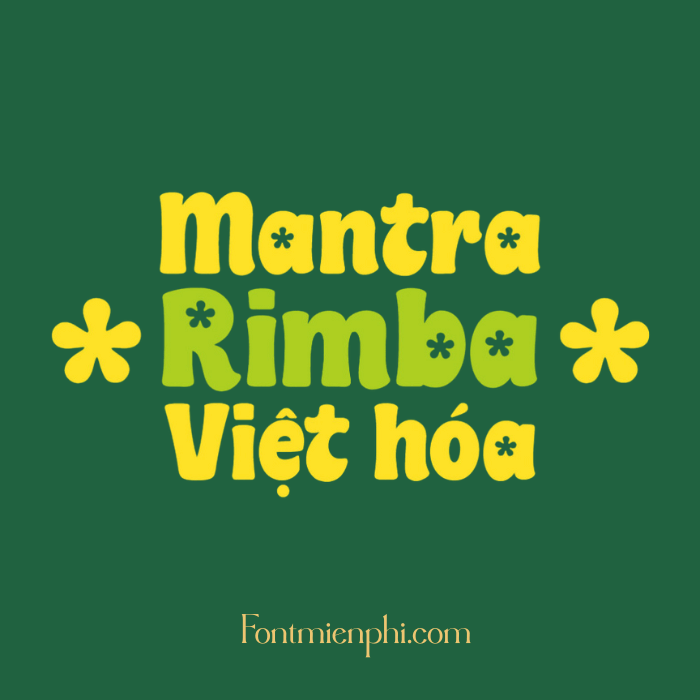
Font Việt hóa 1FTV VIP Mantra Rimba – Phong Cách Độc Đáo Cho Thiết Kế
Font Việt hóa 1FTV VIP Mantra Rimba là bộ font chữ nghệ thuật độc đáo, được thiết kế với phong cách hoang dã, phóng khoáng, phù hợp cho các dự án sáng tạo như poster, logo, bìa sách, và hình ảnh quảng cáo. Với nét chữ uốn lượn tự nhiên, Mantra Rimba mang đến cảm giác mạnh mẽ, cá tính, giúp sản phẩm thiết kế của bạn nổi bật và ấn tượng.
✔️ Phong cách hoang dã, nghệ thuật – Phù hợp với chủ đề thiên nhiên, phóng khoáng.